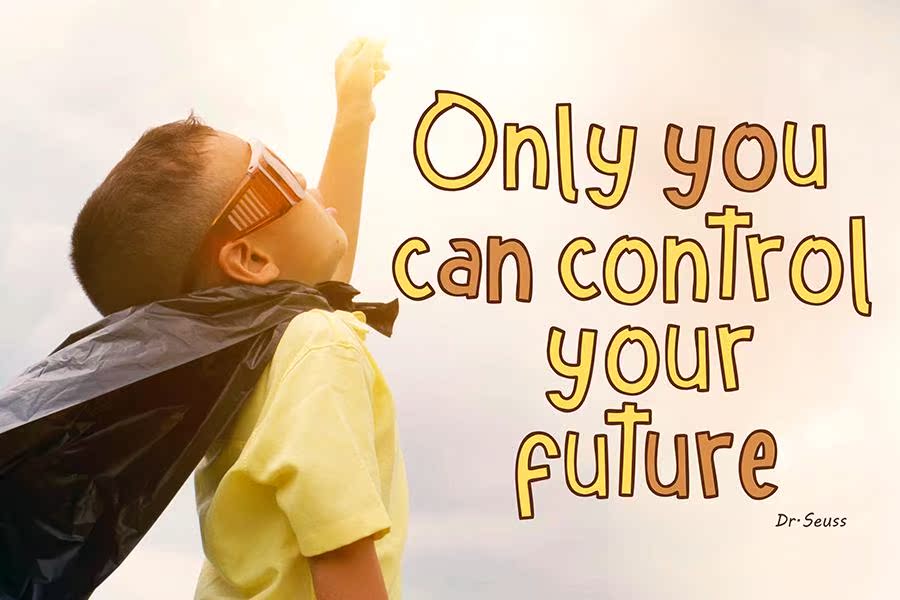
HellofRedayPlayFontIsoFontIsoFontIsoFonts有两种风格,非常有趣。由HellofRedayYouTungLine和HellofReday(纯色)组成。这非常适合于以儿童为主题的设计项目。HellofRedayFont,文具,以及任何需要在两种风格中进行充分书写的项目。